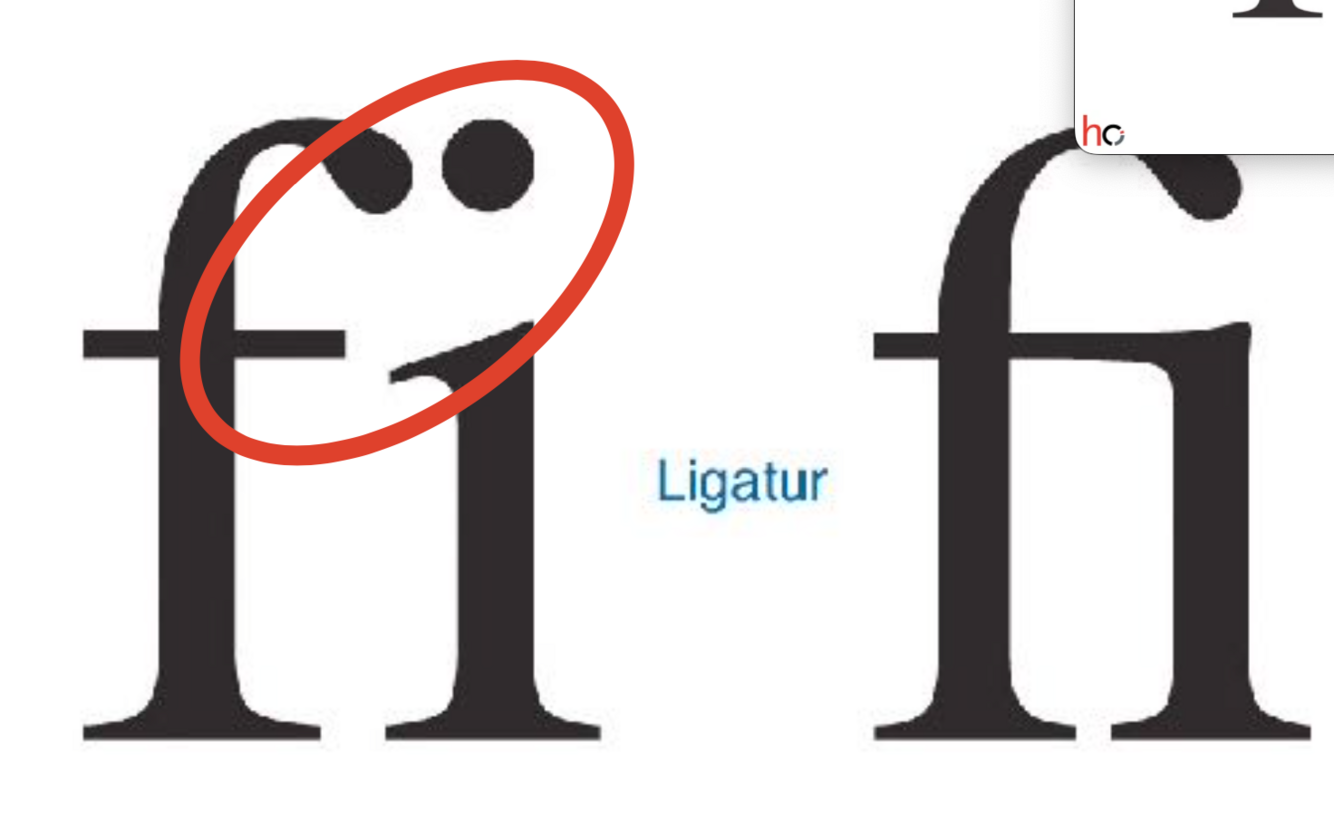
Was bezeichnet Typographie?
Gestaltung des Zeichensatzes z.B. Schriftart
Was ist die Linguistik?
Welche Kategorien an Zeichen gibt es?
Beschreibe Icons
Ein Zeichen, das aufgrund seines Aussehens oder seiner Ähnlichkeit auf etwas Bestimmtes hinweist, wird aufgrund von visueller Ähnlichkeit oder Analogie verwendet.
Beschreibe Symbole
ist Zeichen, bei denen Beziehung zu Denotat arbiträr/konventionell ist
Beschreibe einen Index als Zeichen
Zeichen, das durch direkte reale Beziehung zwischen “Anzeichen” und Objekt konstituiert wird
Welche Beschreibungsebenen von Sprache gibt es?
Wie lange dauert der recognize-act-zyklus?
30-150ms
Auf welchen Strategien basiert Lesen?
Was bedeutet die Multistabilität?
Tendenz zur mehrdeutigen Wahrnehmung
Was bedeutet die Invarianz?
Erkennen einfacher geometrischer Objekte unabhängig von Translation, Ausrichtung etc
Was bedeutet Emergenz?
Erkennen von komplexen Objekten aus einfachen Mustern
Was bedeutet Vergegenständlichung?
Erkennen von räumlichen Strukturen ohne eigentliche Präsentation
Was bezeichnet die Mikrotypographie?
befasst sich mit kleinräumigen Gestaltung des Textsatzes, z.B. Form einzelner Buchstaben
Was sind Ligiaturen?
Was bezeichnet man als Versalien?
Großbuchstaben
Was bezeichnet man als Gemeine?
Kleinbuchstaben
Was bezeichnet mann als Kapitälchen
verkleinerte Großbuchstaben
Wie nennt man die Höhe der Buchstaben m,n,x?
Mittelhöhe
Wie nennt man die Höhe der Buchstaben h,t,f?
Oberlänge
Wie nennt man die Höhe der Buchstaben j,p,q?
Unterlänge
Was bezeichntet man als k-Linie
bezieht die Höhe von größeren Kleinbuchstaben mit ein
Welche Arten von Buchstabenbreiten gibt es?
Was beschriebt Kerning?
beschriebt harmonische Anordnung von Buchstaben, hochwertige Schriften nutzen eine Kerning-Tabelle